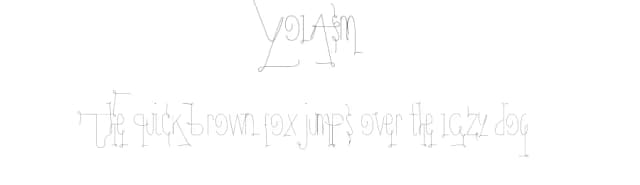
About Queretarotaro Font
Esta es una nueva tipografía basada en la inspiración de un momento de estancia en la Ciudad de Querétaro, México.
Queretarotaro Font
by M#rm#n